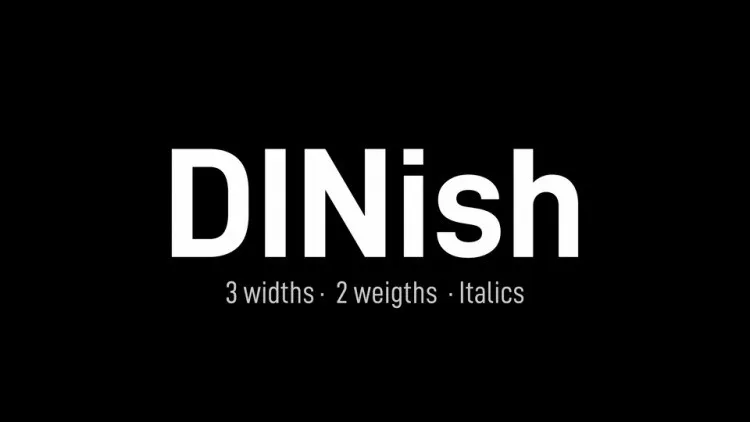
A DINish Font Family é uma opção perfeita para designers buscando uma tipografia sans serif com contraste alto e múltiplas estilos ou pesos, baseada no Altinn-DIN e derivada do Datto’s D-DIN. Esta fonte oferece uma versatilidade que se adapta a vários projetos digitais, desde sites de estilo moderno até cartões de visita elegantes. Com um contraste óbvio entre os elementos da fonte, ela torna o texto fácil de ler em todas as resoluções e tamanhos. Além disso, sua base no Altinn-DIN proporciona um certo conforto visual ao usuário final, mantendo-se contemporâneo sem perder seu caráter tradicional. Ideal para criar ambientes digitais modernos e sofisticados, a DINish Font Family é uma escolha sólida para qualquer projeto em que você deseje transmitir confiabilidade e simplicidade através de um design visual profissional.